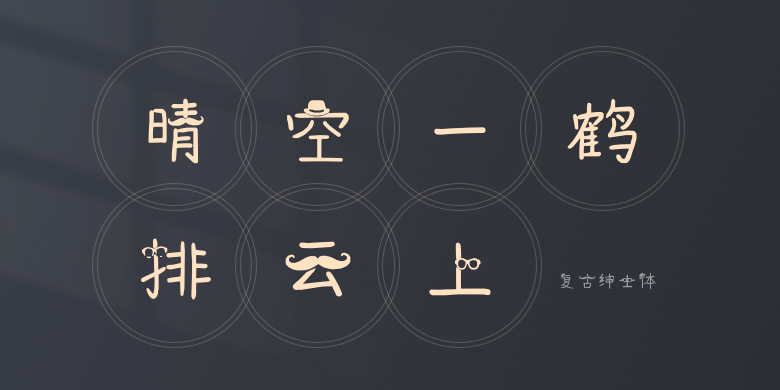
复古绅士体
复古绅士体,这款字体结构工整、笔画清晰,兼顾美观与易读性,适用于标题、正文、海报、包装、LOGO 等多种场景。字形优雅稳定,风格百搭耐看,适配日常排版与创意设计,让文字呈现更舒适、更具质感。复古绅士体一笔一画,皆是细节,以均衡的比例、流畅的线条打造舒适视觉体验,字形端正大气,风格简约现代。无论是商业设计、品牌宣传还是日常排版,都能轻松驾驭,让文字更有格调与力量。复古绅士体字体下载。